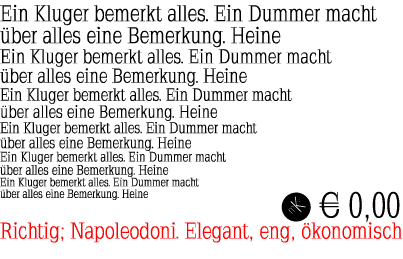
Webfont die Dritte: Font gesucht
zuerst habe ich bei der Schrift des Tagespiegel-Logos auf Times New Roman getippt: http://redir.ec/DFrv
Aber knapp daneben ist auch vorbei. Gibt es die Schrift auch als Webfont?
Ich kenn sie nicht, hab aber ein größeres Bild für euch …
wird, auch wie bei der Süddeutschen auch nur das Logo geben, denk ich – kann mich aber sehr wage dran erinnern, mal nen Freefont beim stöbern gesehen zu haben, der sehr ähnlich war.
Ich habe das Logo einfach mal http://www.whatfontis.com/ vorgeworfen:
Hmmm ... sieht Schei*e aus? Aber da war noch was ... Schriften von Manfred Klein?
Und die passen von den Serifen her nicht ... Na ja, ein letzter Versuch?
Es könnte eine von diesen Schriften gewesen sein. :-?
war zumindest lange (ich weiß nicht ob sie mittlerweile einem Redesign zum Opfer gefallen ist) die Californian (gibts u.a. bei LTC) und der Titel war aus deren bold-Schnitt gesetzt. Diese Internetlogofassung könnte auch das Ergebnis einer Vergewaltigung mittels Stauchen und Verzerren dieser eigentlich sehr schönen Druckschrift sein ...
Das hat jetzt aber eher weniger mit dem gesuchten Beispiel zu tun …